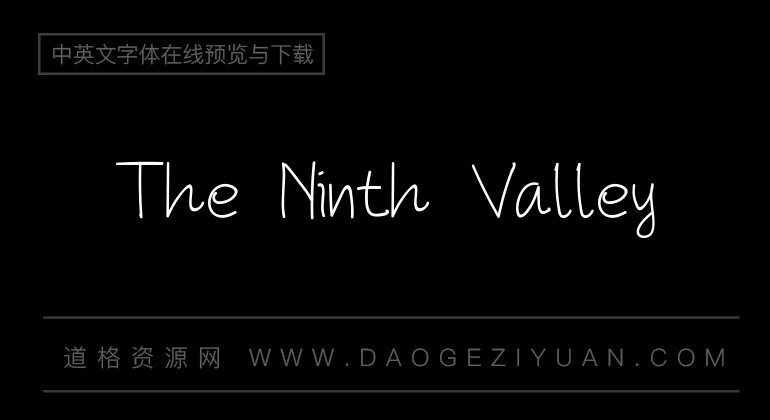
The Ninth Valley 是一款由 Font Fabric 公司设计的字体,它是一种自由洒脱的手写体字体,具有独特的魅力,令人印象深刻。字体可以用于各种类型的设计,包括海报、标志、书籍、杂志等。它具有细腻的笔画、清晰的字形和平衡的空间感,可以为您的设计创造出精美的外观。内容介绍
The Ninth Valley是一款非常不错的手写艺术字体,具有很好的视觉感,适合于文化类的宣传设计、商业类品牌的广告和产品包装设计以及个性化文字排版等较多场景。